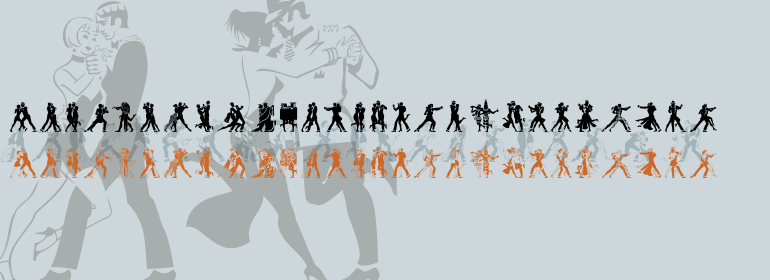
Linotype Tangomaniacs™
Linotype Tangomaniacs™,这款字体结构工整、笔画清晰,兼顾美观与易读性,适用于标题、正文、海报、包装、LOGO 等多种场景。字形优雅稳定,风格百搭耐看,适配日常排版与创意设计,让文字呈现更舒适、更具质感。Linotype Tangomaniacs™一笔一画,皆是细节,以均衡的比例、流畅的线条打造舒适视觉体验,字形端正大气,风格简约现代。无论是商业设计、品牌宣传还是日常排版,都能轻松驾驭,让文字更有格调与力量。Linotype Tangomaniacs™字体下载。
字体品牌: Linotype(Monotype) 设计师:Garcia,Victor 字体分类:衬线体 字体属性:外文 字符集:Unicode 发布时间: 2018